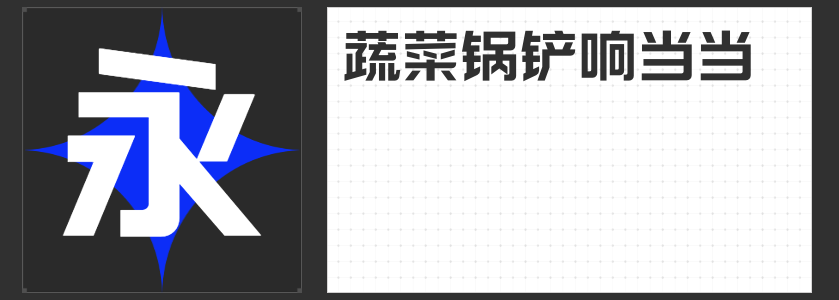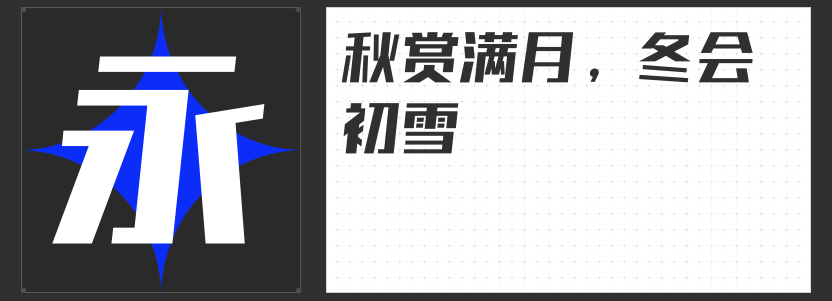
舌尖上的艺术:精致字体为美食书籍添彩
无论是烹饪指南还是美食故事集,一本优秀的美食书籍不仅仅是关于食谱的罗列,更是一场视觉与味觉的盛宴。恰当的字体选择能够让书籍的内容更加生动有趣,为读者带来非凡的阅读体验。在这里,我们特别推荐四款适合用于美食书籍设计的字体,它们各具特色,定能为您的美食书籍增添一抹独特的风味。
1. 励字勇敢黑简 大黑 —— 极简主义下的大气磅礴
“励字勇敢黑简 大黑”是一款极简主义风格的大黑体。它的设计简洁有力,字形方正,笔画粗犷,适合用作书籍标题或章节开头的字体。当应用于美食书籍时,这款字体能够为食谱目录或是重点菜式的介绍带来一种稳重而不失大气的感觉。无论是经典佳肴还是创新料理,在“励字勇敢黑简 大黑”的衬托下,都能够展现出独特的魅力,吸引读者的目光。
2. 高手庆科帅黑体 大黑 —— 强烈对比中的精致美感
“高手庆科帅黑体 大黑”以其强烈的对比度和独特的设计感而闻名,它既保留了黑体的基本特征,又通过细节处理赋予了字体更多个性。对于美食书籍而言,这种字体非常适合用来强调某些特别的环节,如特别推荐的菜品介绍、食材来源的故事或是主厨背后的小秘密。它能够有效地抓住读者的眼球,传递出每一道菜肴背后的故事和情感,让阅读变成一次心灵与味蕾的旅行。
3. 造字侠郝刚快乐简 微黑 —— 温馨家庭厨房的笔触
“造字侠郝刚快乐简 微黑”是一款充满温馨感的手写体,字形略显圆润,给人一种亲切友好的感觉。在设计美食书籍时,这样的字体非常适合用于描述家常菜的做法或者记录与食物有关的家庭回忆。它能够营造出一种温馨和谐的氛围,让读者仿佛置身于充满爱意的家庭厨房之中,体验到烹饪的乐趣与亲情的温暖。
4. 字恋狂澄空 絮风 —— 坠入甜品点心的漩涡
“字恋狂澄空 絮风”是一款风格可爱的创意字体,每一笔每一划都透露着可爱与随性的气息。如果您的美食书籍有甜品点心的模块,那么这款字体将是最佳选择。无论是介绍精致的蛋糕,还是可爱的饼干的制作教学,“字恋狂澄空 絮风”都能以其独特的笔触,为文字增添一抹可爱与甜蜜,引领读者进入一个充满想象的世界。
字体的选择对于美食书籍来说至关重要,它不仅影响着书籍的整体风格,还关系到内容传达的有效性。上述四款字体各有千秋,能够根据不同类型的美食书籍和具体需求灵活运用,为读者呈现出一场视觉与味觉的双重盛宴。希望这些建议能够帮助您在未来的美食书籍设计中,找到最合适的字体搭配,创造出令人难忘的作品。